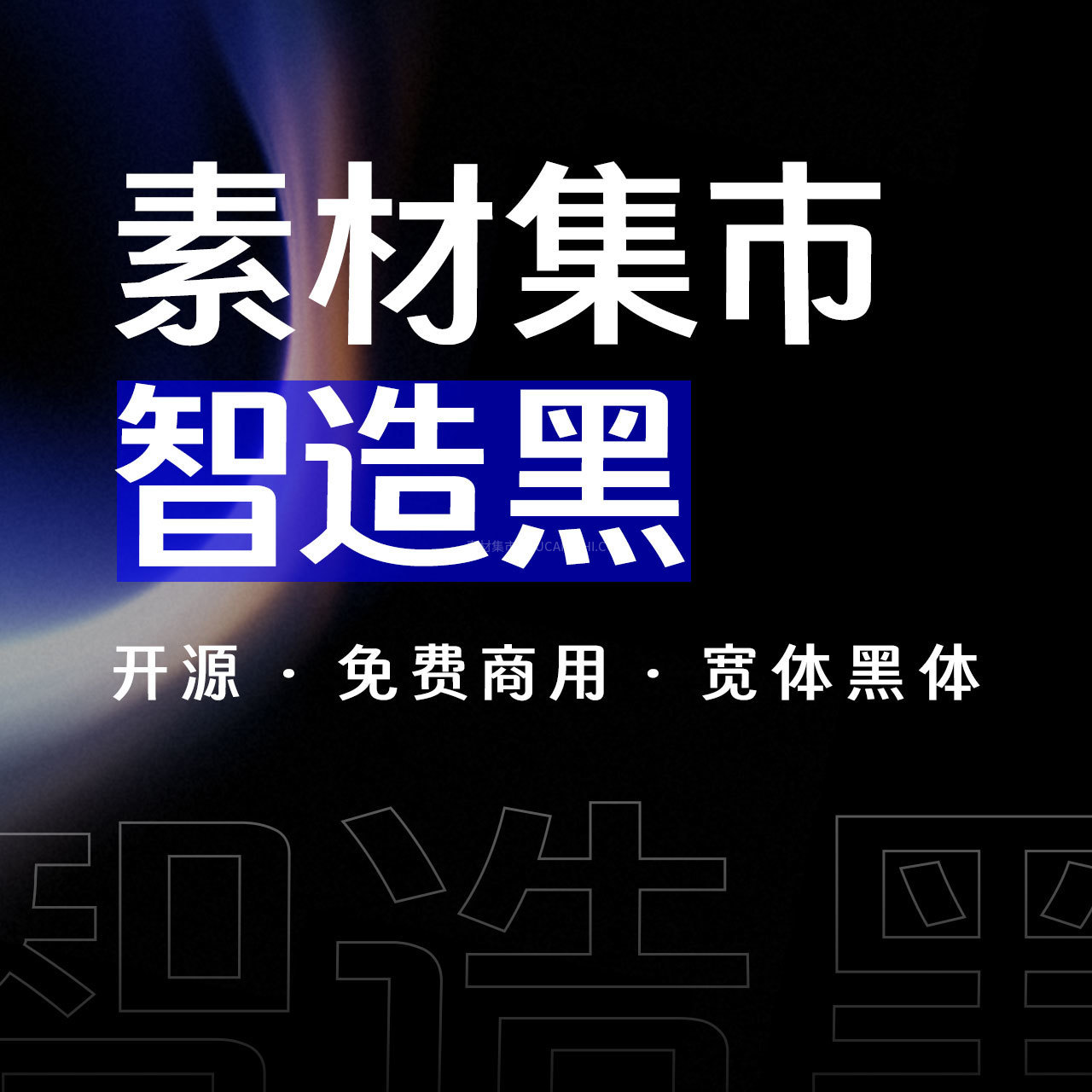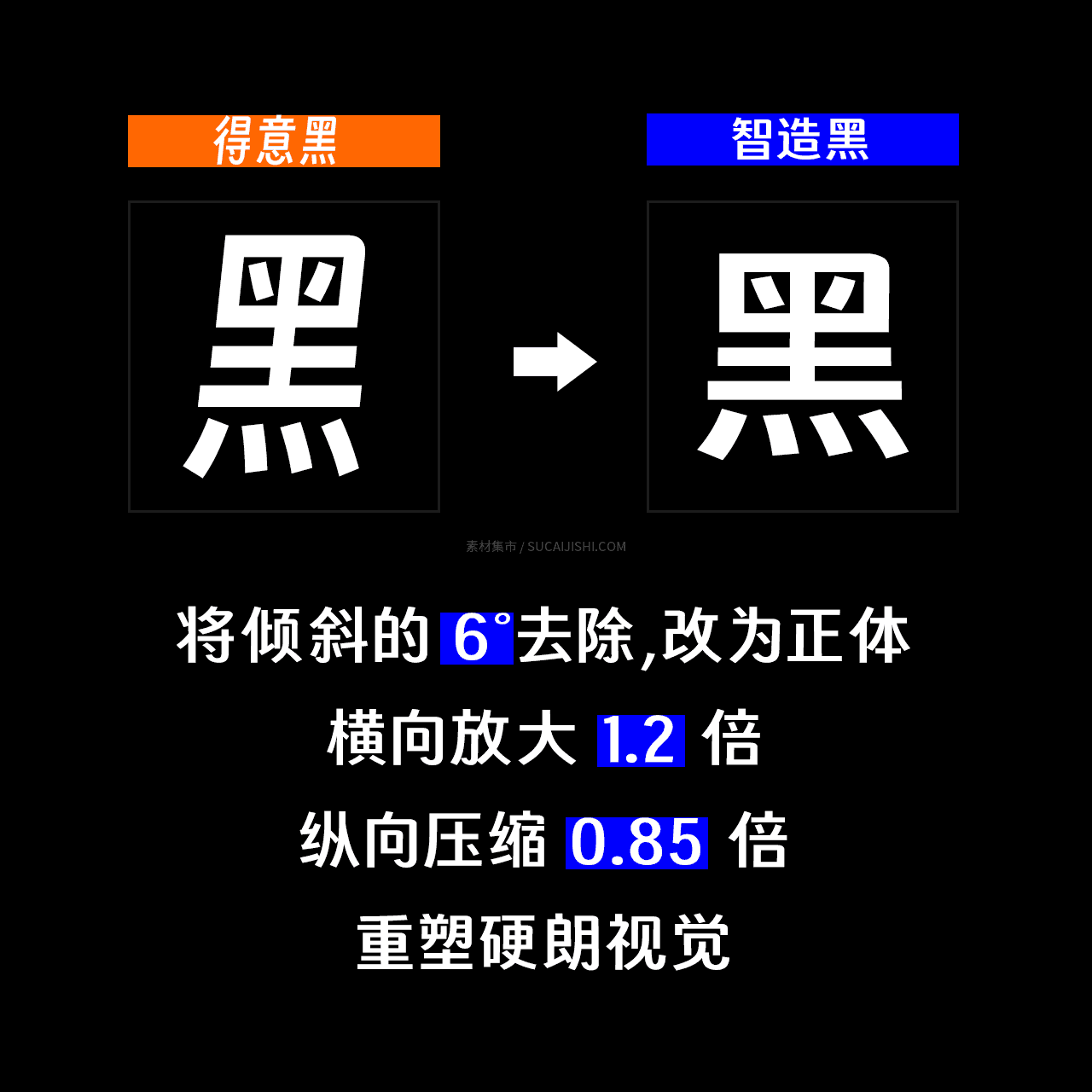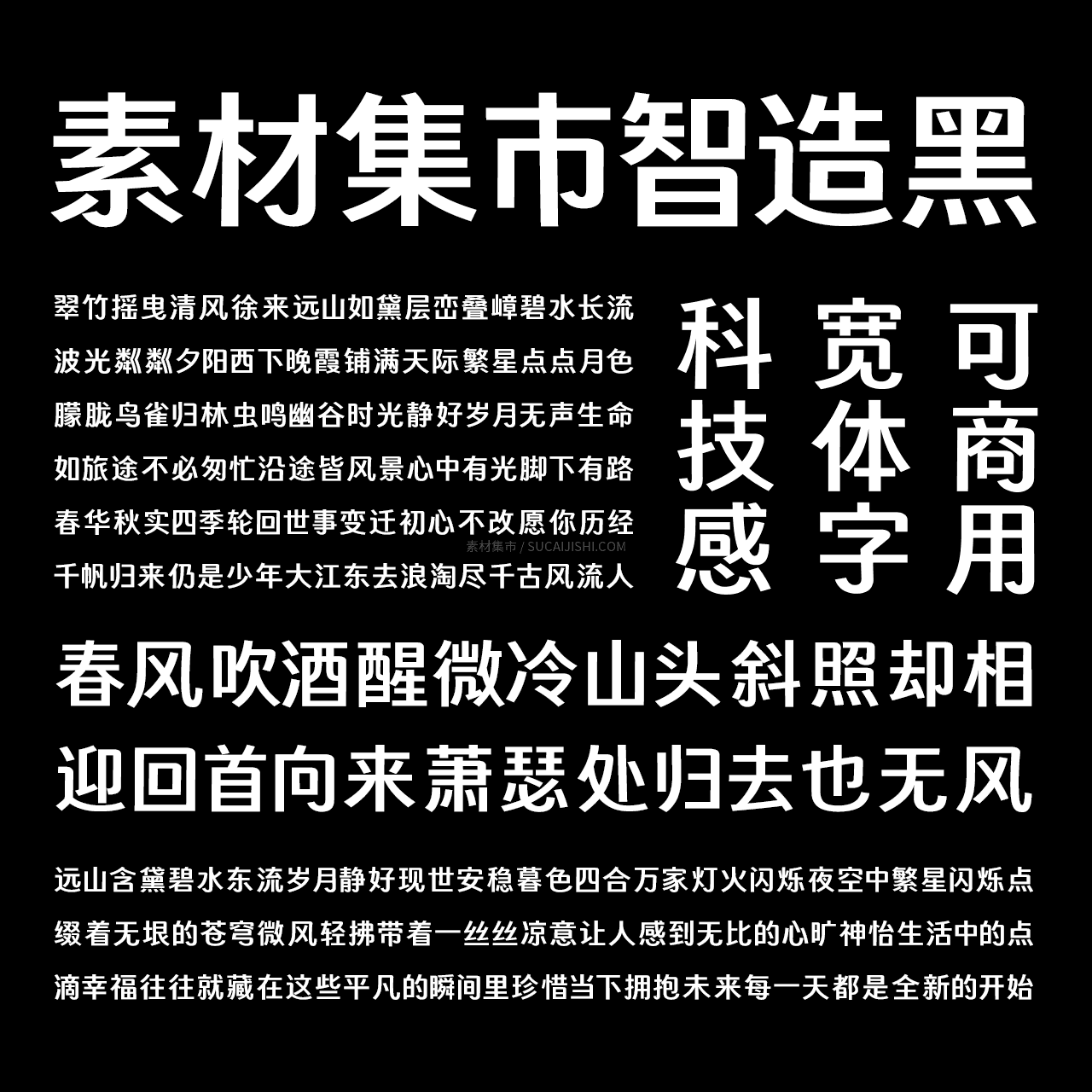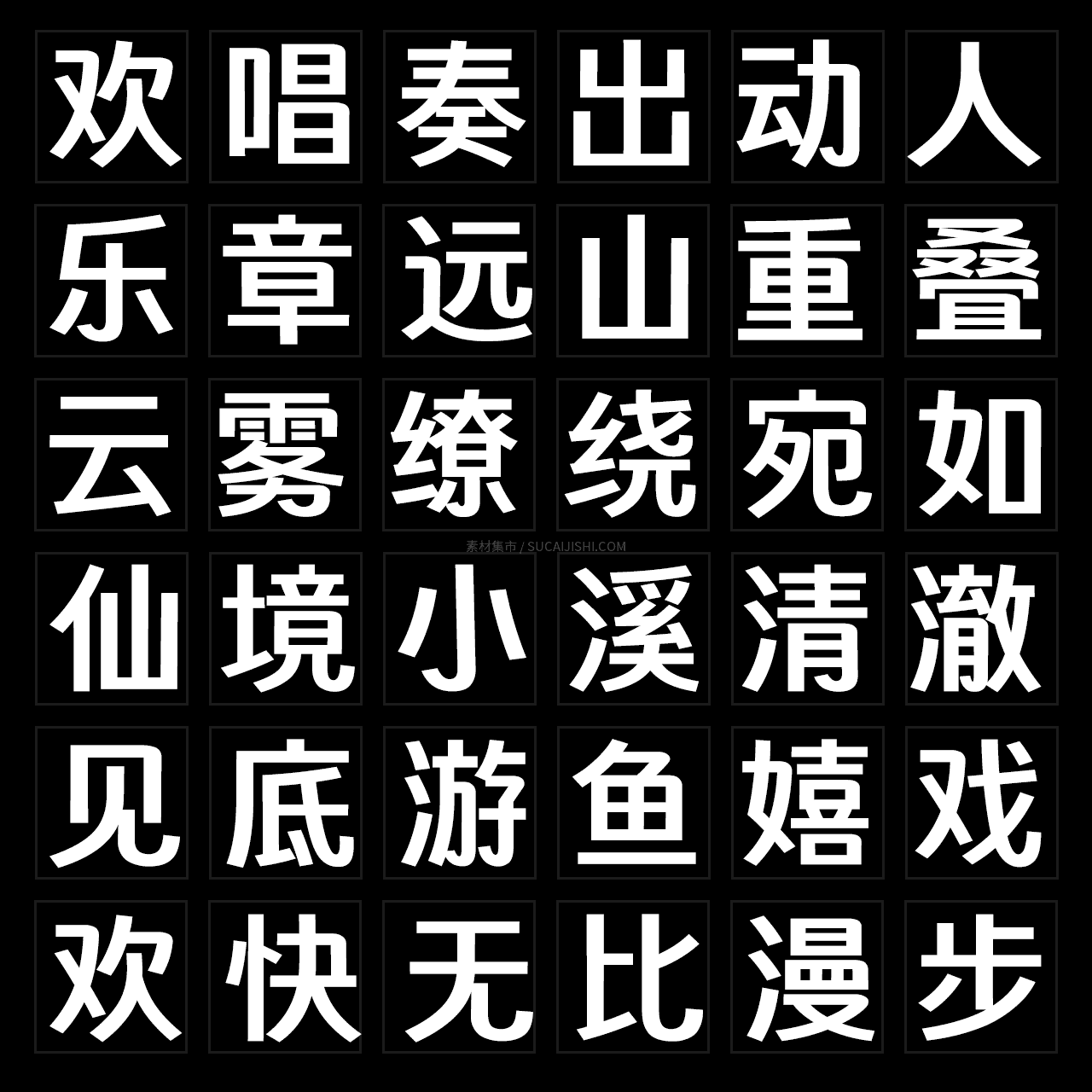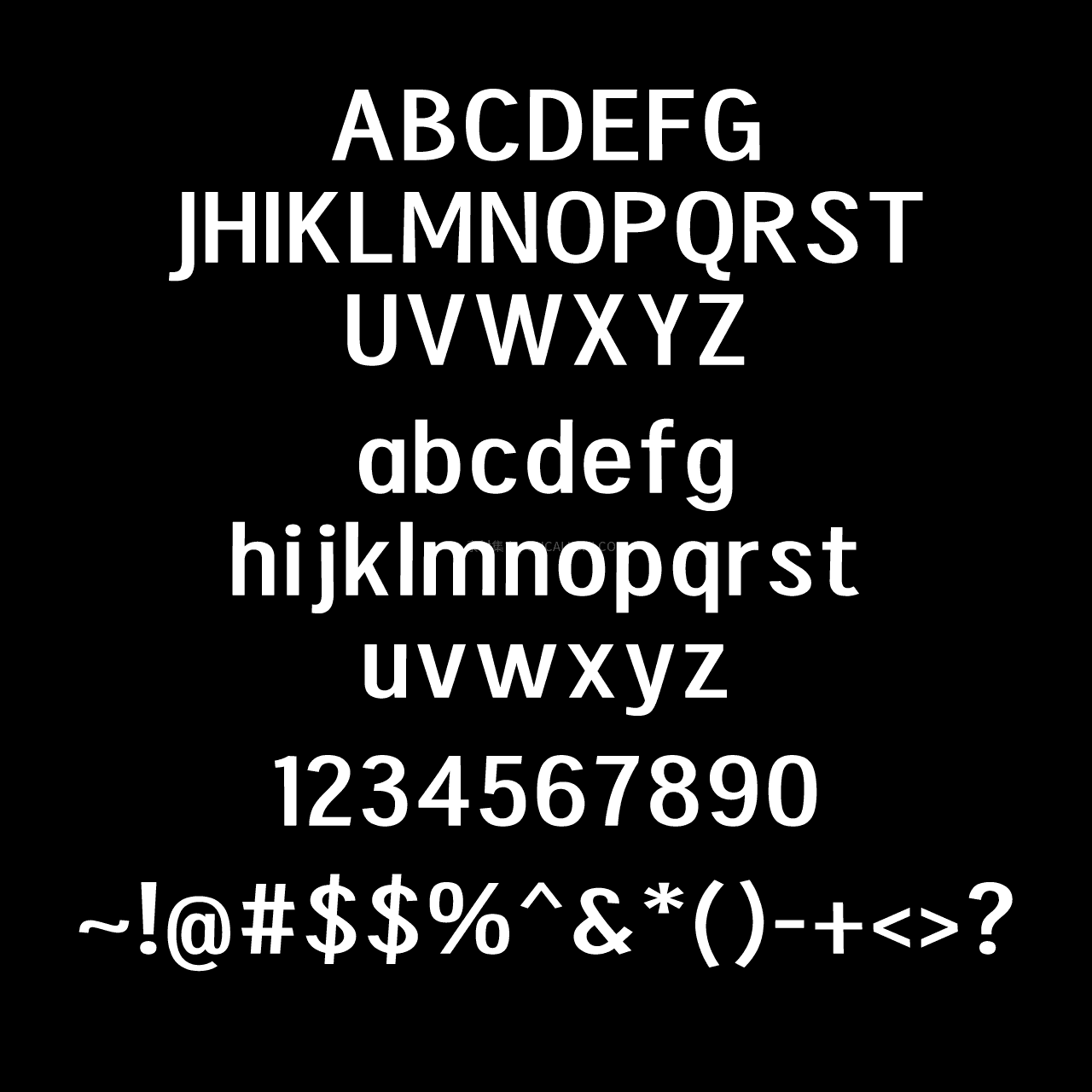
素材集市智造黑
素材集市智造黑是一款基于开源字体「得意黑」进行二次创作的中文字体。字体在原有字形基础上重新调整了笔画结构、倾斜角度与整体比例,将原本具有一定跳跃感的字形重新塑造成更加稳定、硬朗的宽体黑体。简洁的无衬线结构搭配舒展的横向比例,使字体在视觉上呈现出鲜明的力量感与现代感,尤其适合需要强调标题视觉与文字张力的设计场景。
从字形表现来看,智造黑最大的特点在于稳定而宽阔的字体结构。设计过程中对原字体的倾斜感进行了重新处理,将倾斜的字形调整为更加接近正体的视觉状态,同时对横向与纵向比例进行重构,使文字整体更加舒展。经过横向放大与纵向压缩之后,字体形成了具有辨识度的宽体特征,字面空间更加开阔,横向延展的视觉效果也让标题文字显得更加厚重、有力。
反向拉直: 抹除原版跳跃的倾斜感,施加 -6 度反向拉直,并向右补偿横向重心,让每个字都能稳稳扎根。宽体比例: 采用“横向拉宽 1.2 倍、纵向压扁 0.85 倍”的重构比例,极大拉升了字面的开阔度与视觉张力。这种设计并没有过多加入装饰性的笔画变化,而是通过比例、重心与结构来塑造字体个性。因此,智造黑既保留了黑体清晰直接的阅读特征,又拥有区别于常规黑体的视觉气质。尤其是在较大的字号下,字体粗壮的笔画与宽阔的字面能够形成较强的视觉冲击力,让短标题、品牌名称和宣传文案更加醒目。
在整体气质上,素材集市智造黑偏向现代、硬朗、理性与工业感。规整的结构让字体拥有较强的秩序感,而宽体比例又避免了传统黑体过于紧凑的视觉效果。放置在深色背景中时,粗壮的字形能够形成明确的视觉轮廓;应用于海报、Banner、品牌标题等大字号排版时,也能够展现出较强的视觉存在感。
除了中文字体设计之外,智造黑还针对多语言排版进行了较为完整的字符补充。字体包含较丰富的中文字符,同时加入拉丁字母、日文平假名与片假名,以及基础西里尔字母、希腊字母等字符。不同语言之间采用相对统一的视觉风格,在进行中英文、中日文以及部分多语言混排时,可以减少字体风格不统一带来的割裂感,让整体排版更加协调。
智造黑的应用范围也比较广泛。它适合用于品牌标题、科技设计、工业制造、产品宣传、活动海报、网页 Banner、包装设计以及新媒体视觉等场景。特别是在需要突出力量感、科技感或现代感的设计中,宽体字形能够有效增强文字的视觉重量。相比一些强调个性装饰的字体,智造黑更加注重字体本身的结构表现,因此在不同设计主题中也拥有较好的适应性。
对于喜欢现代黑体、宽体字体以及工业风视觉的设计师来说,素材集市智造黑可以作为标题字体和展示字体使用。无论是用于一句简短有力的标题,还是作为品牌视觉中的核心文字,它都能够凭借自身较强的字面张力,为设计增加更加鲜明的现代感。
总体而言,素材集市智造黑并不是简单地改变字体粗细,而是通过对原有字形比例和视觉重心进行重新塑造,让字体从偏灵动的视觉风格转向更加稳定、宽阔的现代黑体风格。宽体结构带来的开阔感、硬朗笔画带来的力量感,以及简洁无衬线结构所带来的现代气质,共同构成了这款字体鲜明的视觉特点。